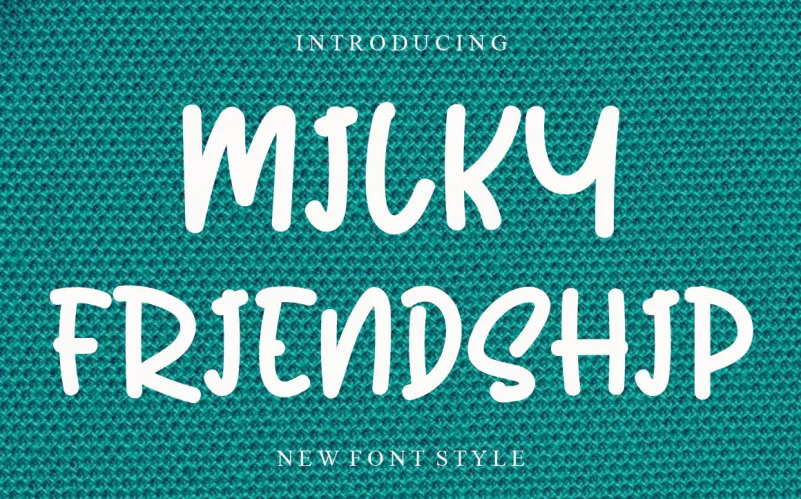
A Milky Friendship Font é uma fonte escrita a mão única e divertida que traz ao seu design uma paleta vibrante e descontraída. Seja para fazer postagens engraçadas no Instagram ou para projetos de calligrafia casuais, esta fonte transformará suas ideias criativas em obras de arte memoráveis. A Milky Friendship Font é o parceiro perfeito para qualquer trabalho que você está iniciando, seja uma mensagem pessoal, um aniversário especial ou até mesmo a decoração de uma festa. Ideal tanto para quem busca adicionar um toque personalizado ao seu material digital quanto para os amantes da arte tradicional em busca de algo diferente e descontraído. A Milky Friendship Font é perfeita para qualquer designer, sejam eles profissionais ou iniciantes, que buscam uma fonte moderna com a qualidade de uma escrita delicada e familiar.